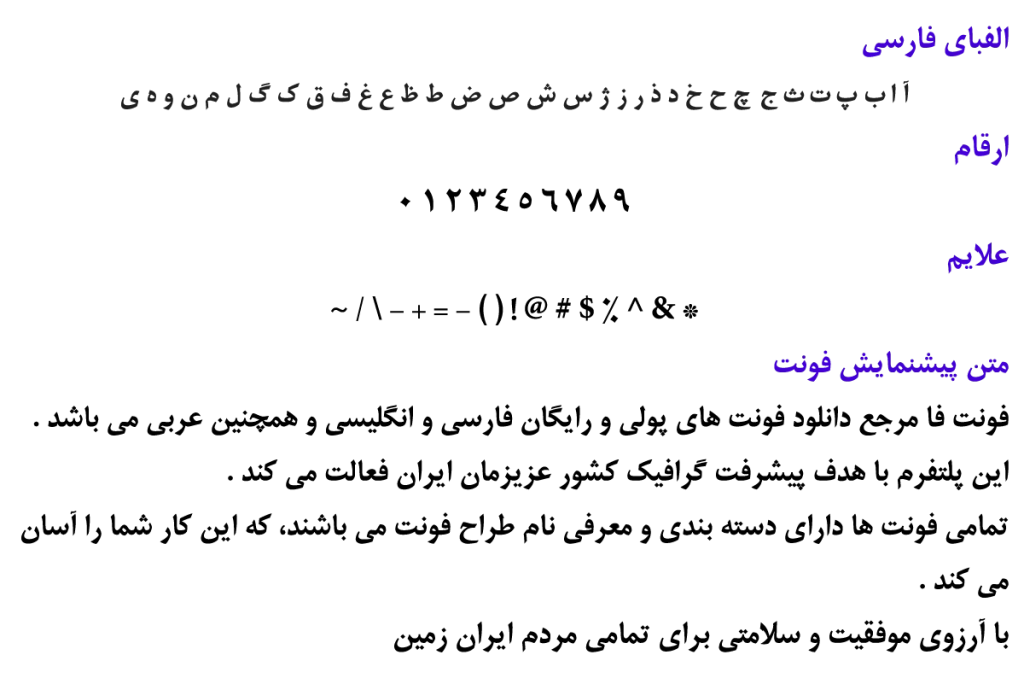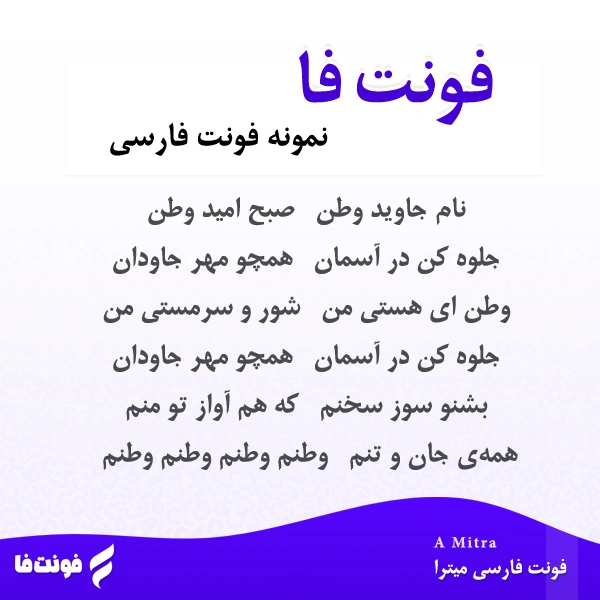
فونت فارسی میترا – A Mitra
سال ساخت فونت: 1387
نوع فونت: فونت عنوان
پیشنمایش فونت میترا
توضیحات و معرفی فونت میترا
فونت فارسی میترا ( A Mitra ) از مجموعه فونت های آزاد می باشد، و نیز نوع فونت عنوان می باشد.
فونت خوشگل مربوط در سال 1387 طراحی و ساخته شده است.
این فونت دارای 5 نوع استایل نوشتاری می باشد.
و نیز فونت A Mitra در یک وزن پر رنگ است.
در تصویر زیر، پیش نمایشی از این تایپ فیس را همراه با شعر زیبای فارسی میبینید.